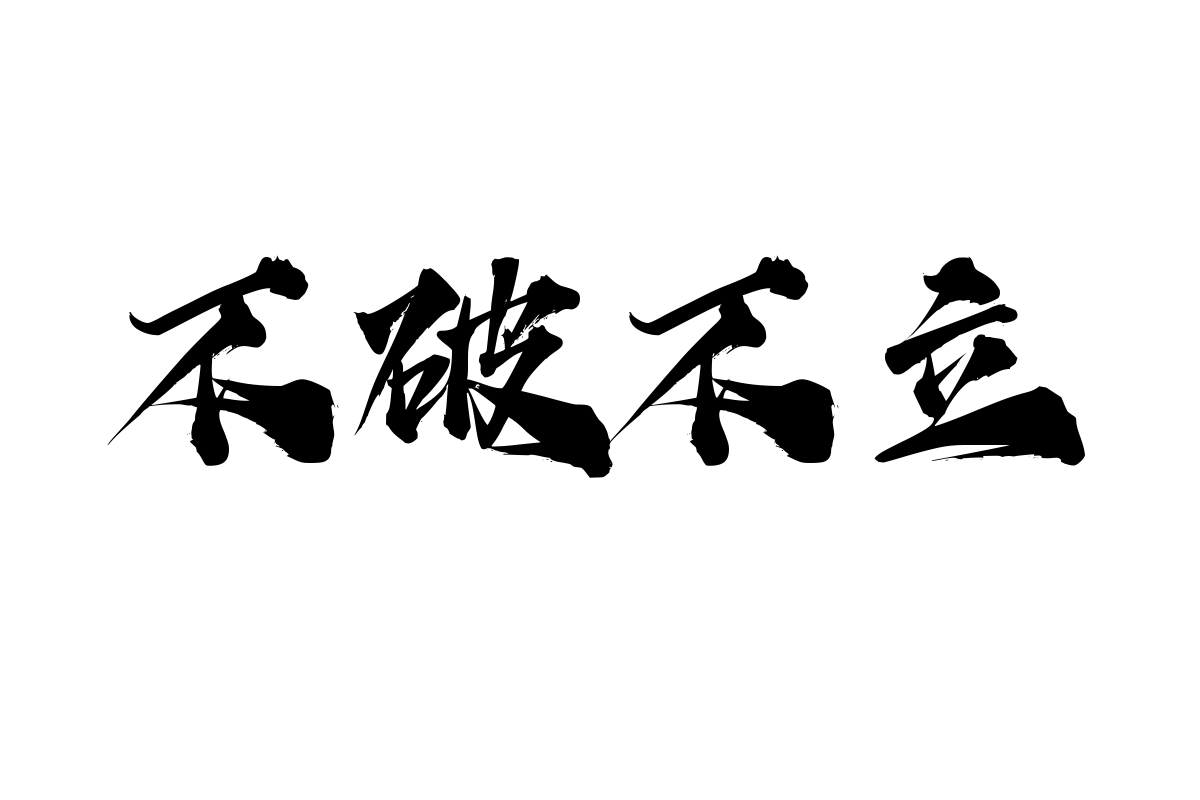
潮字社霸王枪简体版是一款具有独特风格的字体,其特点如下:
1. 字形结构:该字体采用了传统的汉字结构,笔画流畅,线条清晰。每个字的笔画都经过精心设计,使得整体字形显得饱满而有力。
2. 风格特点:潮字社霸王枪简体版具有浓厚的武侠气息,适合用于武侠、仙侠等题材的文字设计。同时,该字体也具有较强的视觉冲击力,能够吸引读者的注意力。
3. 应用场景:该字体适用于需要强调武侠氛围的文字设计,如武侠小说、武侠电影海报、武侠游戏界面等。此外,还可用于一些需要突出个性和创意的场合,如广告宣传、个人博客等。
总之,潮字社霸王枪简体版是一款具有独特风格的字体,适用于需要强调武侠氛围的文字设计。